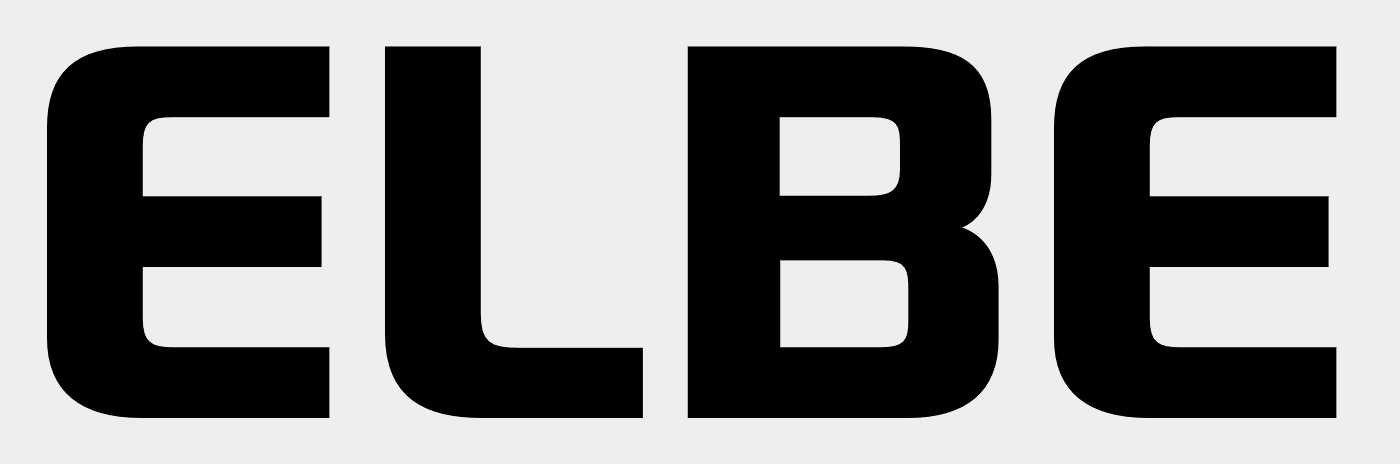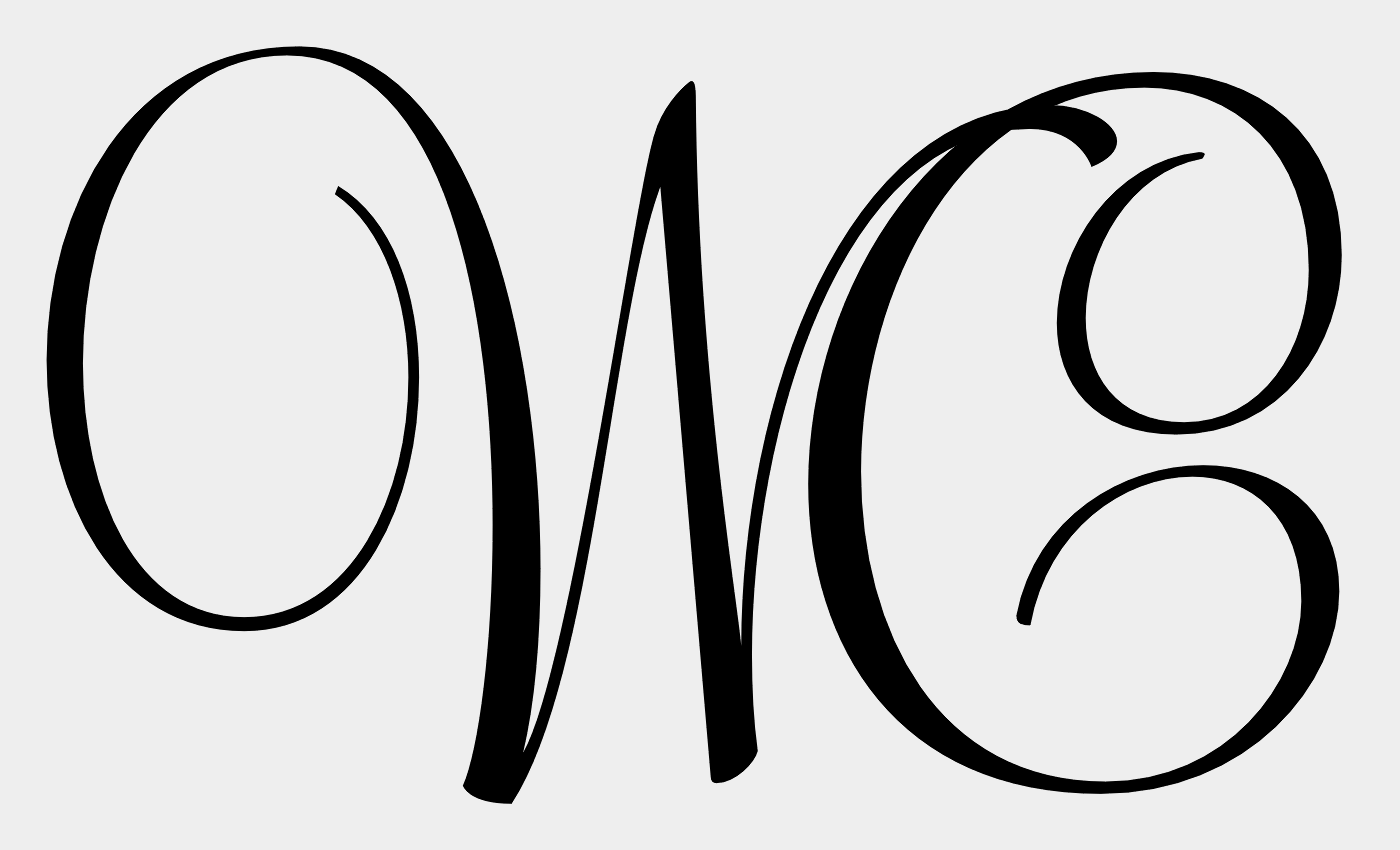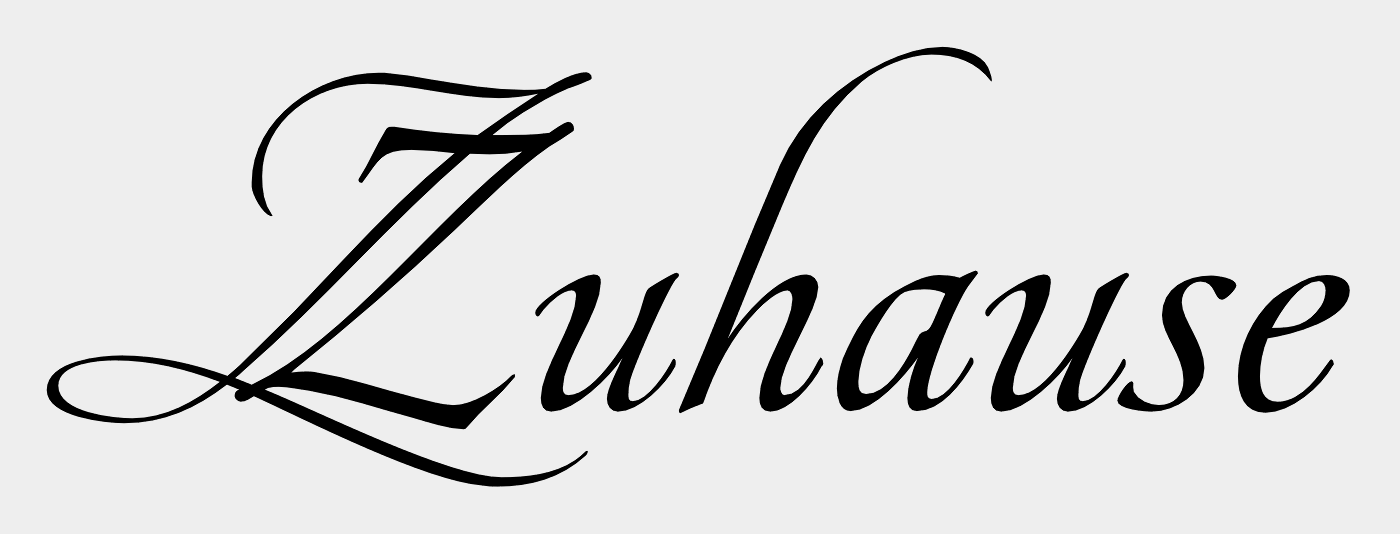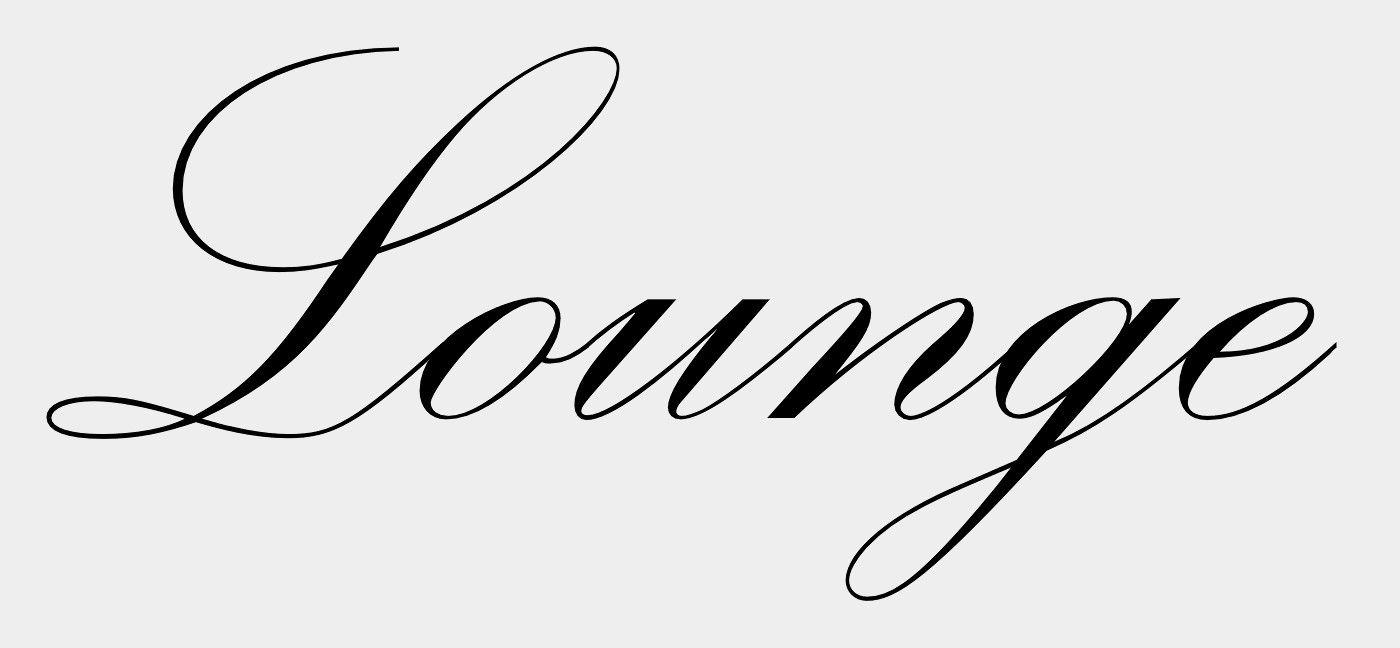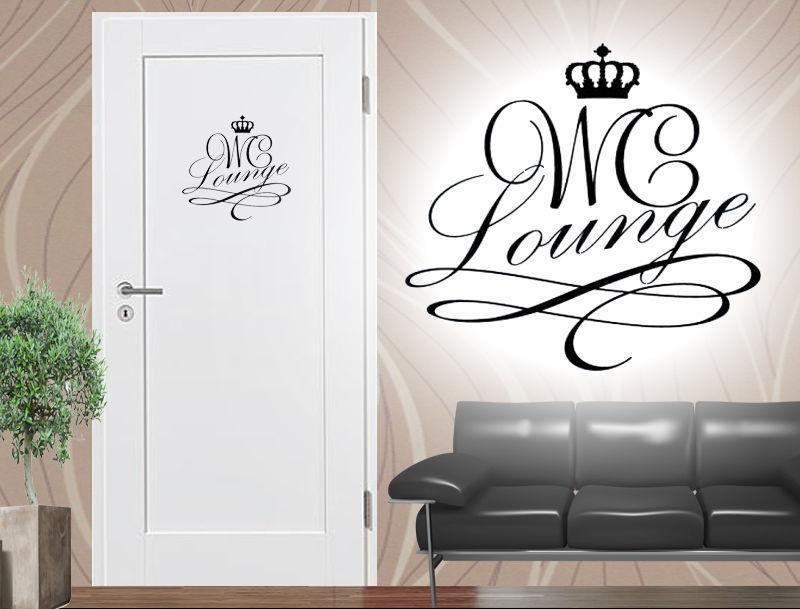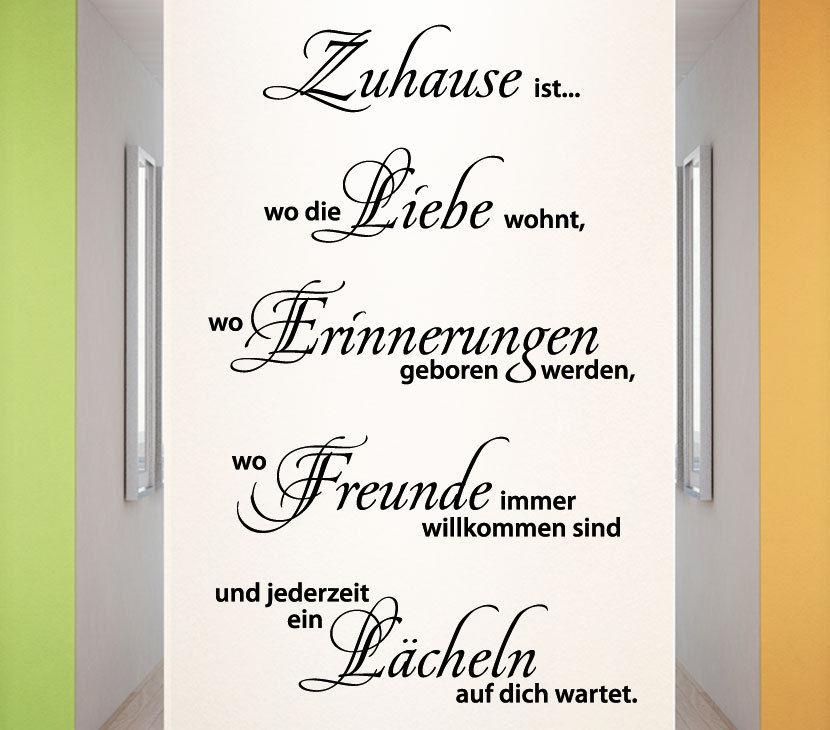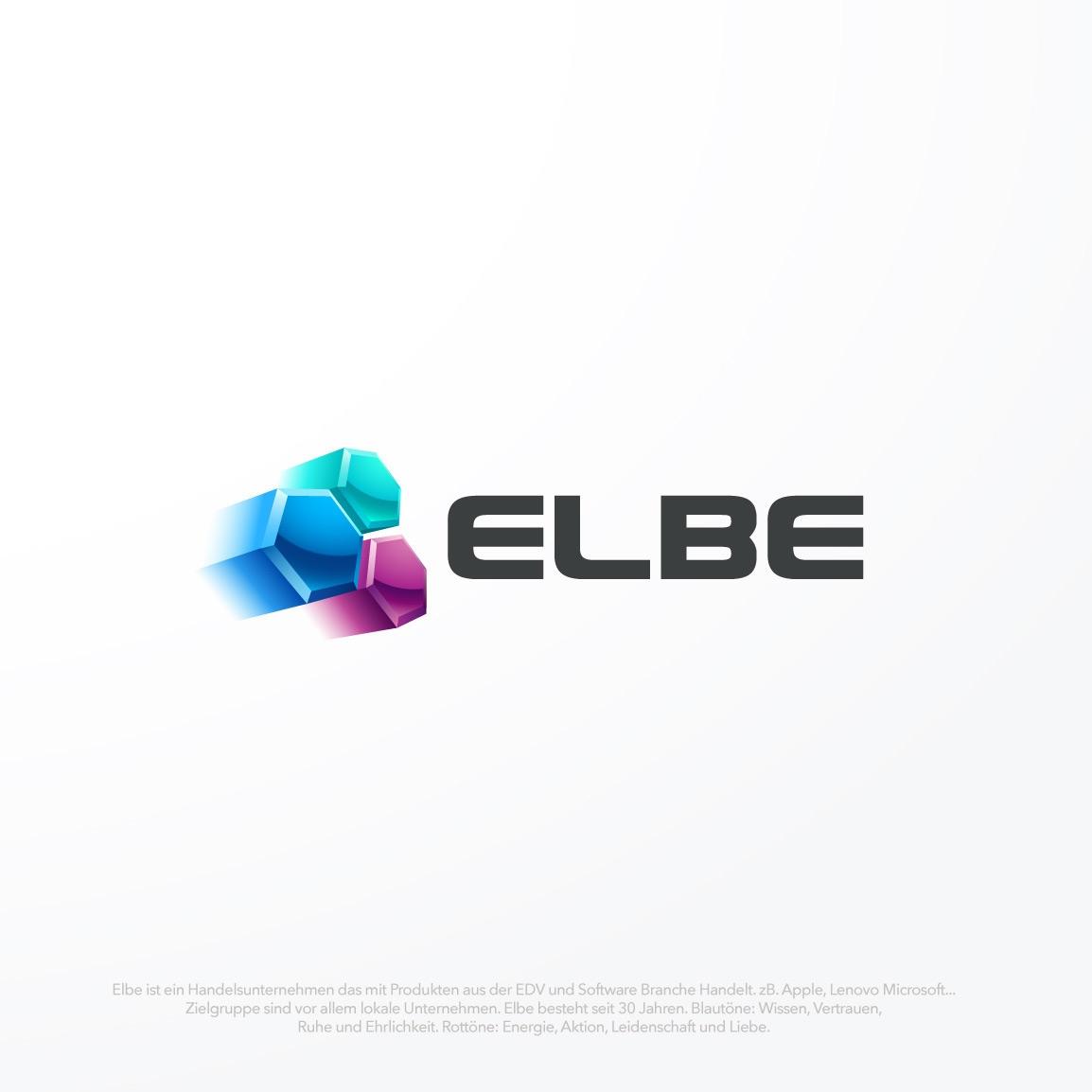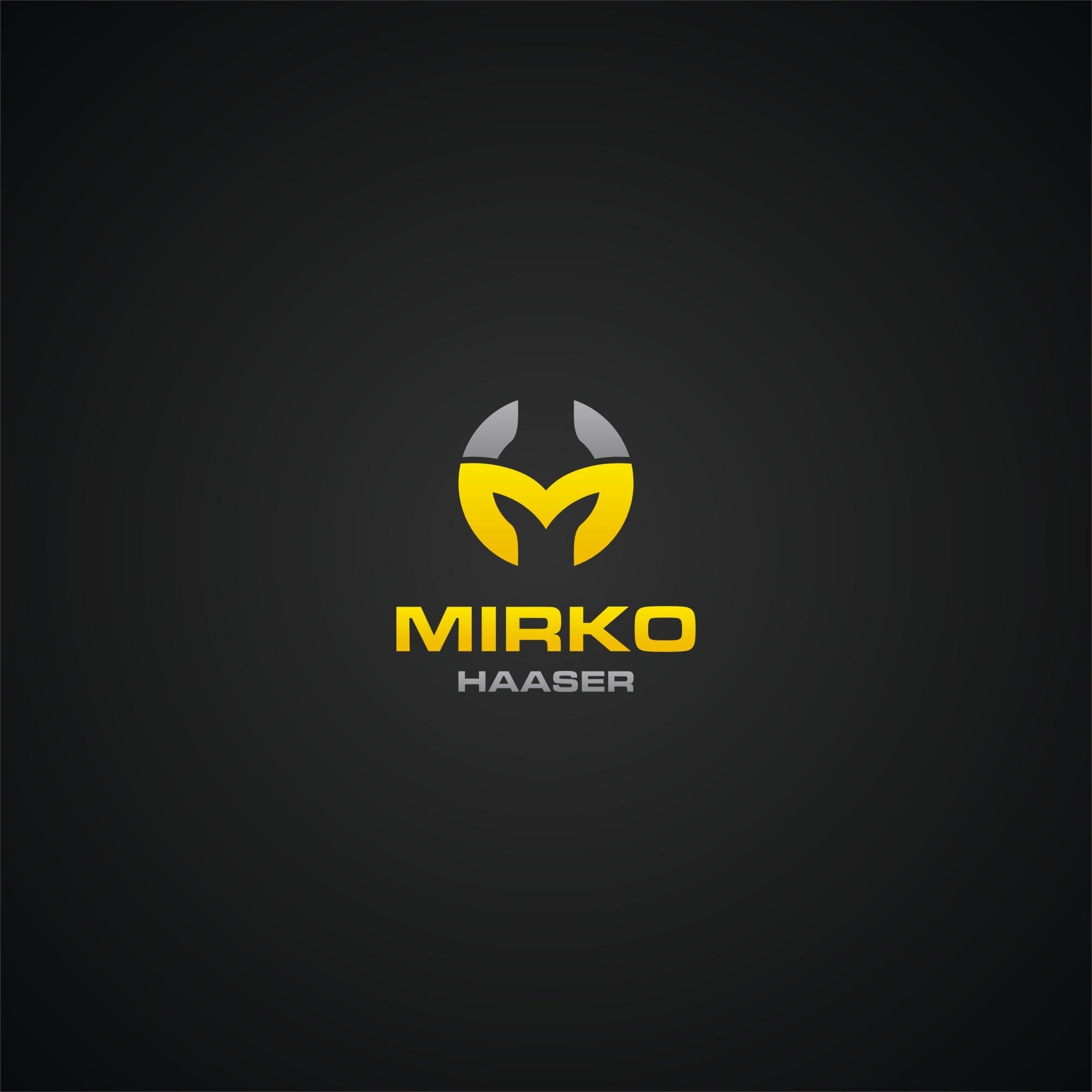
Ich hätte da 4 Fonts wo ich gerne den Namen wissen würde!
ELBE sieht aus wie eine verzerrte
bei dem ersten bild (feel script), denkt du ist ist das WC und Lounge die selbe Schrift? Ich suche speziell die glyphe vom "L"...
müsste das sein, das geschwungene L wird sich als Alternative darin befinden.
Aber die Schriftmischung auf dem Schild mit dem Zuhause-Spruch tut mir weh, die Serifenlose passt überhaupt nicht zu der geschwungenen Schreibschrift (von dem fehlenden Leerzeichen vor den Auslassungspunkten will ich jetzt gar nicht reden (obwohl ich es damit ja doch getan habe).